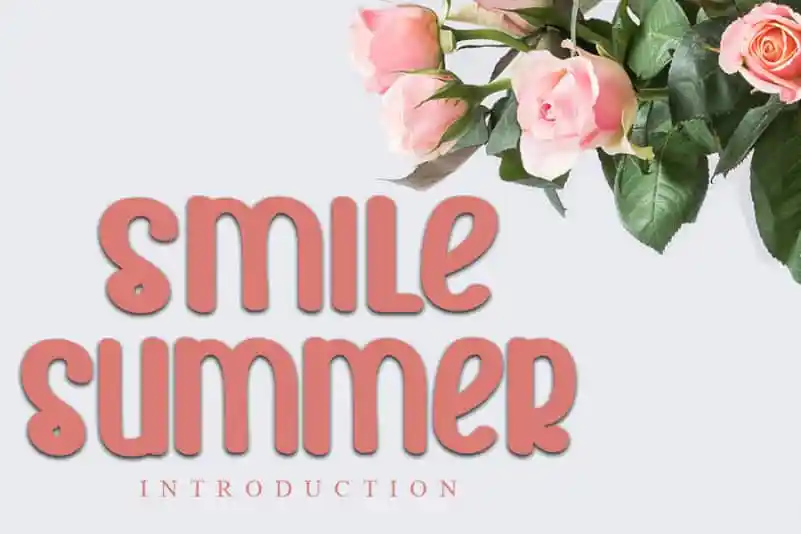
Smile Summer Script Font
A Smiley Summer Script é uma fonte escrita a mão que transmite alegria e frescura ao mesmo tempo. Inspirada nos antigos estilos de caligrafia, mas atualizada para um sentimento contemporâneo e atual, esta fonte pode ser usada em uma ampla variedade de ideias criativas. Ela é perfeita tanto para adicionar personalidade a cartões de assinatura ou títulos, quanto para estilizar itens de papelaria. Com seu charme antigo revigorado e sua sensação moderna e vibrante, esta fonte será uma escolha excelente para os amantes da escrita a mão que buscam um toque único em seus projetos gráficos.